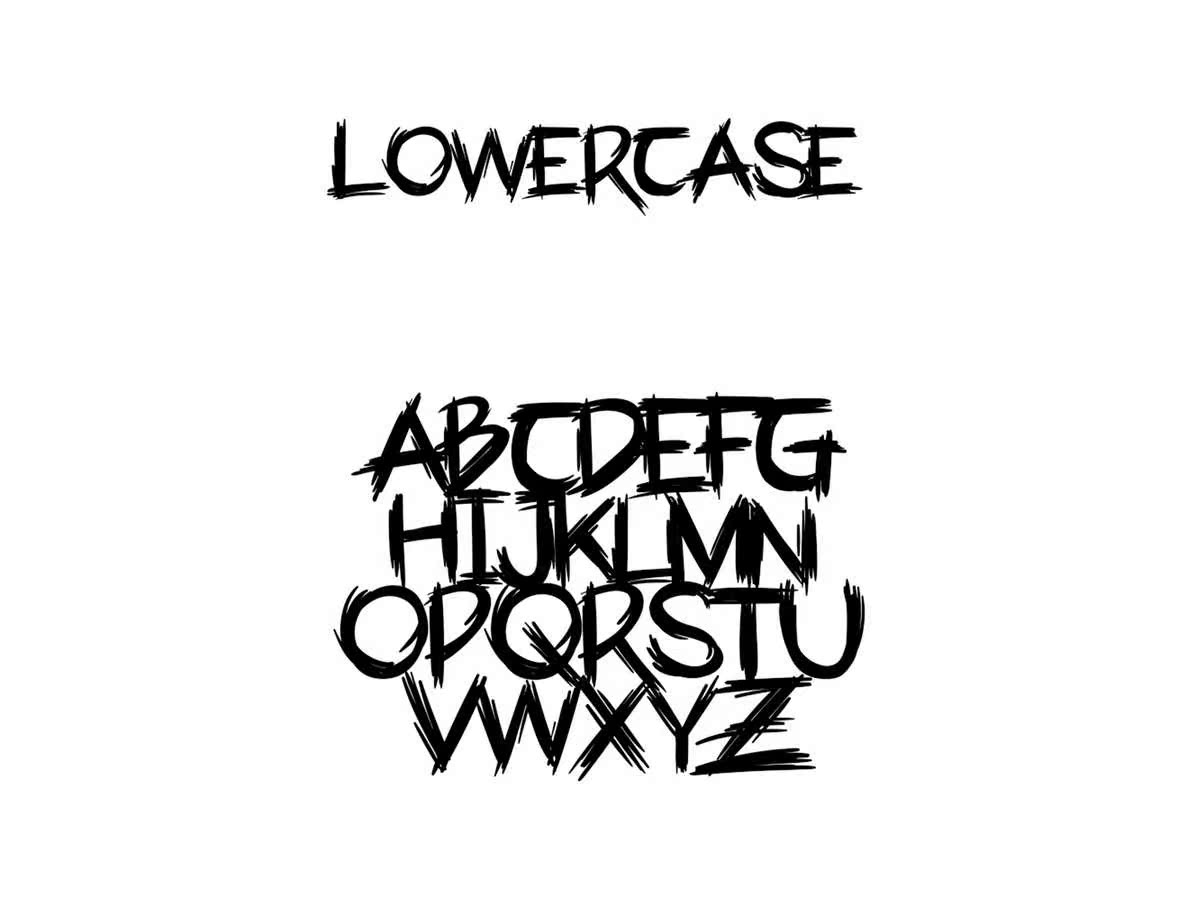
来自Apriellat、Brokered和GrimFeelCharacterSet的RGHIS新字体。要创建组合,只需探索正则或斜体,有两种样式和规则。韩国ComicorWebToon上的RGHIS Spirefroms Screen。来自Apriellat、Brokered和GrimFeelCharacterSet的RGHIS新字体。要创建组合,只需探索正则或斜体,韩国ComicorWebtoon上的Arghin Spirefroms CreamScreen有两种样式,分别为Alic和Regular。